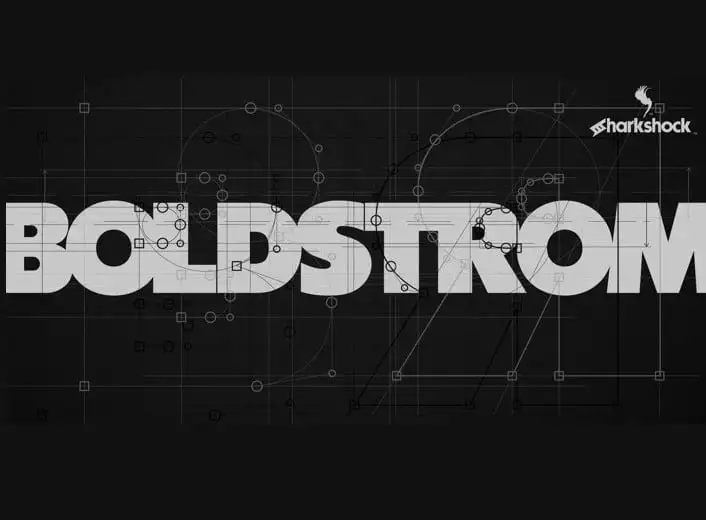
Boldstrom Sans Serif Font – Download Grátis
A Boldstrom Sans Serif é uma elegante tipografia sans-serif que transmite modernidade e força, ideal para designs que buscam destaque. Ela foi criada por um designer chamado sharkshock no site 99designs. Este tipo de fonte é especialmente adequada para usos visuais impactantes como títulos em grandes formatos impressos, capas de livros e até mesmo logotipos de empresas, graças a seu uso intenso dos espaços vazios entre as letras. Características marcantes incluem linhas grossas, tipografia inteiramente em caixa alta e curvas apertadas. O design também foca na minimização do contraste para enfatizar os caracteres, garantindo que estejam bem alinhados uns com os outros. Isso ajuda a reduzir espaçamentos desnecessários enquanto também cria uma tensão visual necessária para transmitir o poder e a vitalidade que esta fonte oferece. A Boldstrom é perfeita para qualquer projeto que precisa de destaque, seja um logotipo inovador em uma capa de livro ou uma gráfica agressiva em uma película de cinema. Seja qual for o seu propósito visual, essa fonte certamente trará o foco necessário ao seu design.